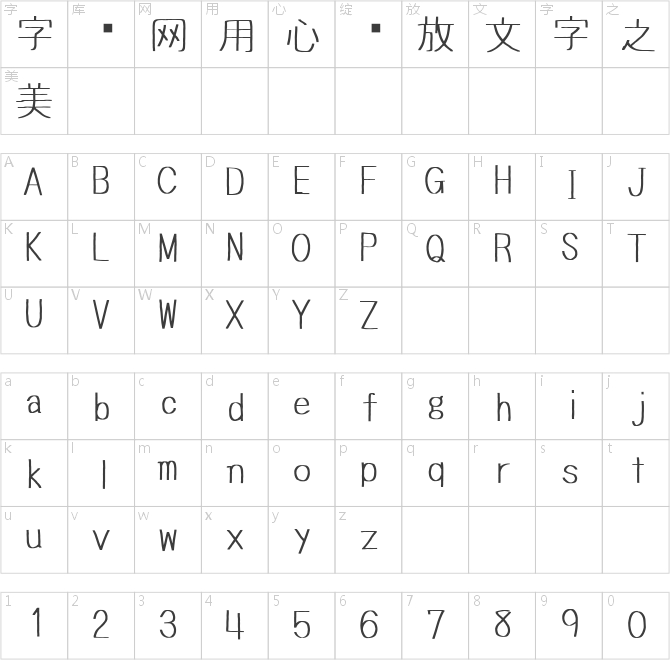
九ちゃんフォント字體下載kyutyan小九手寫(xiě)體kyuchan_Font
小九手寫(xiě)體是一款筆畫(huà)非常幼細(xì)的日系免費(fèi)商用字體。字體的風(fēng)格纖細(xì),就像女孩子寫(xiě)的字體,特別適合用于女性,兒童,偏可愛(ài)風(fēng)格的海報(bào)設(shè)計(jì)。可以作為正文文字和印刷物等的素材使用。
九ちゃんフォント字體kyutyan小九手寫(xiě)體kyuchan_Font 字庫(kù)是一款讓人賞心悅目、百看不厭的日文字體,適合各類(lèi)廣告和產(chǎn)品包裝設(shè)計(jì)應(yīng)用,字體大小4.36MB,格式為ttf字體,上傳用戶(hù)是23KUN,作者/版權(quán)方為隠れ家